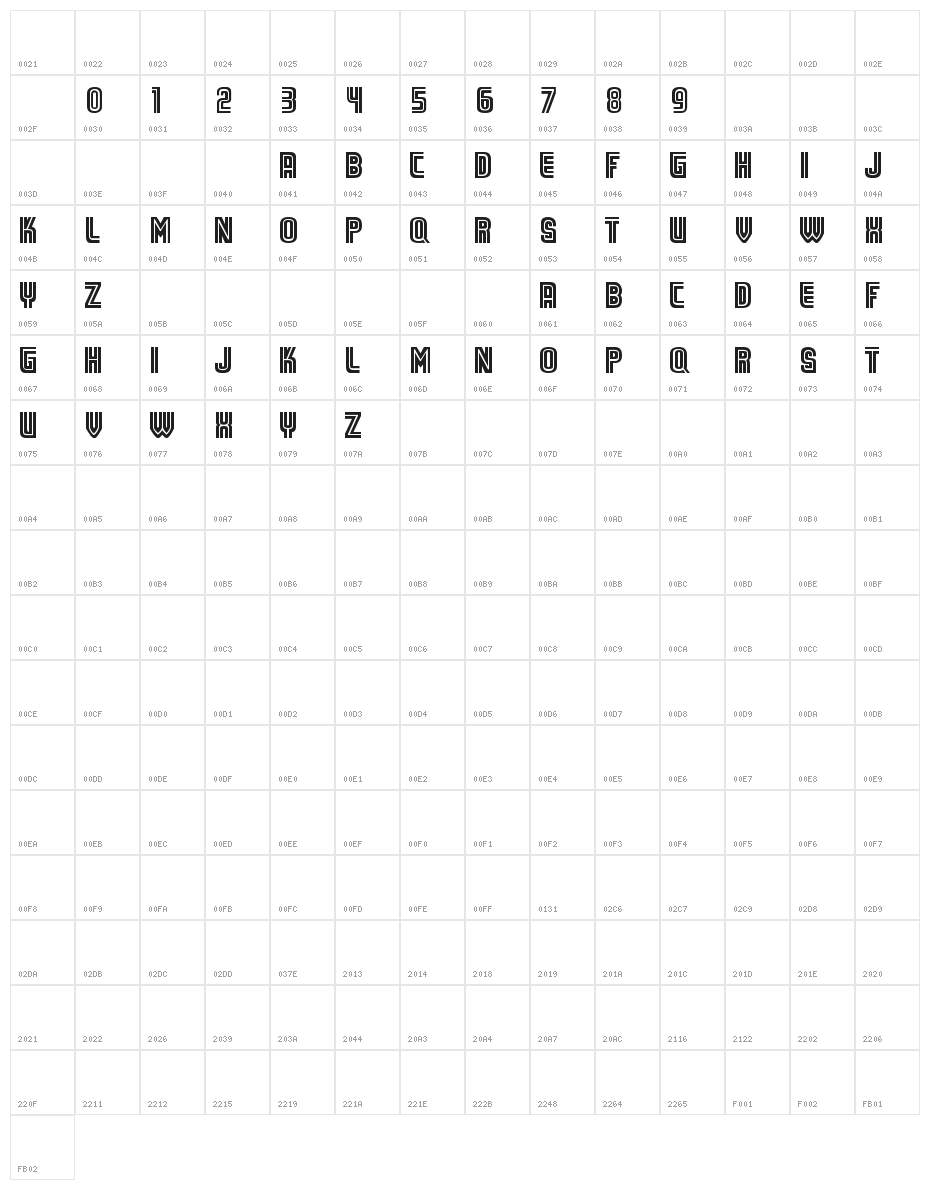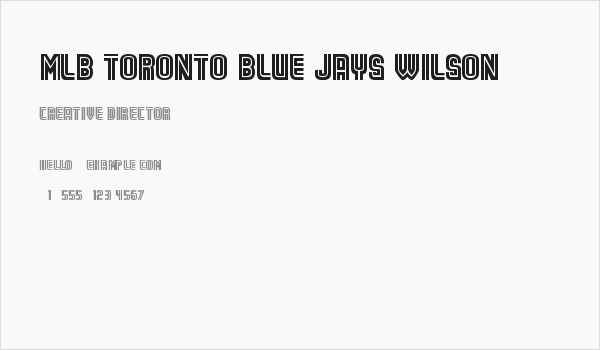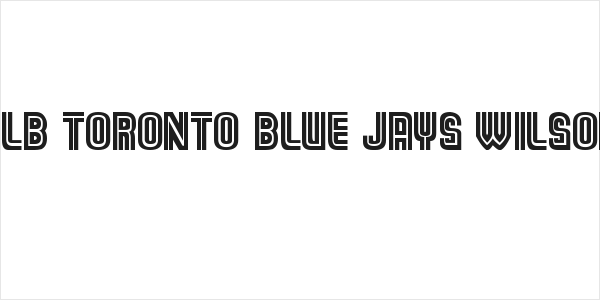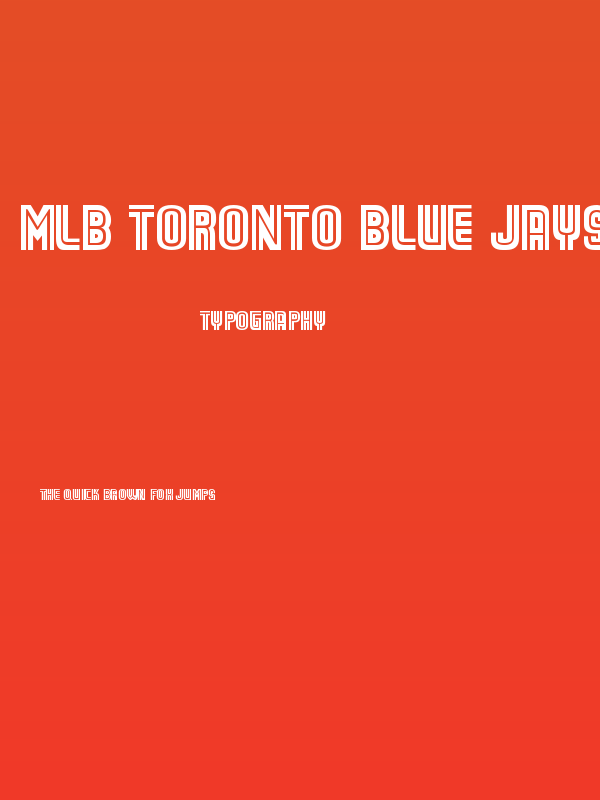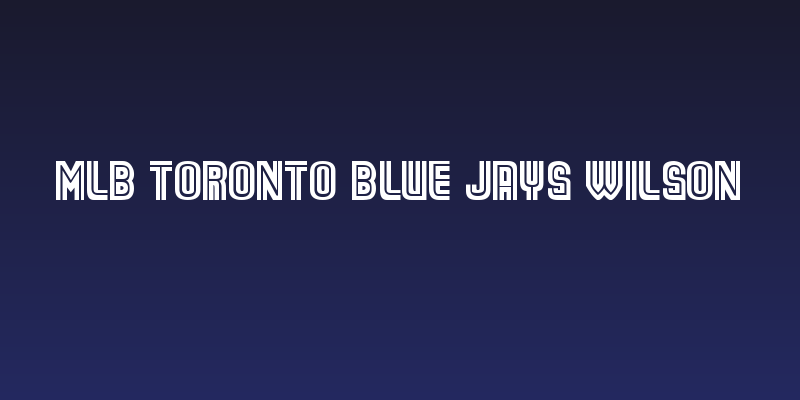
MLB Toronto Blue Jays Wilson Font
| Nome | MLB Toronto Blue Jays Wilson |
| Categorie | sports |
| Caso d'uso | Logos, Headlines |
| Progetti proposti | Perfect for sports team logos, merchandise branding, posters, and event promotions. |